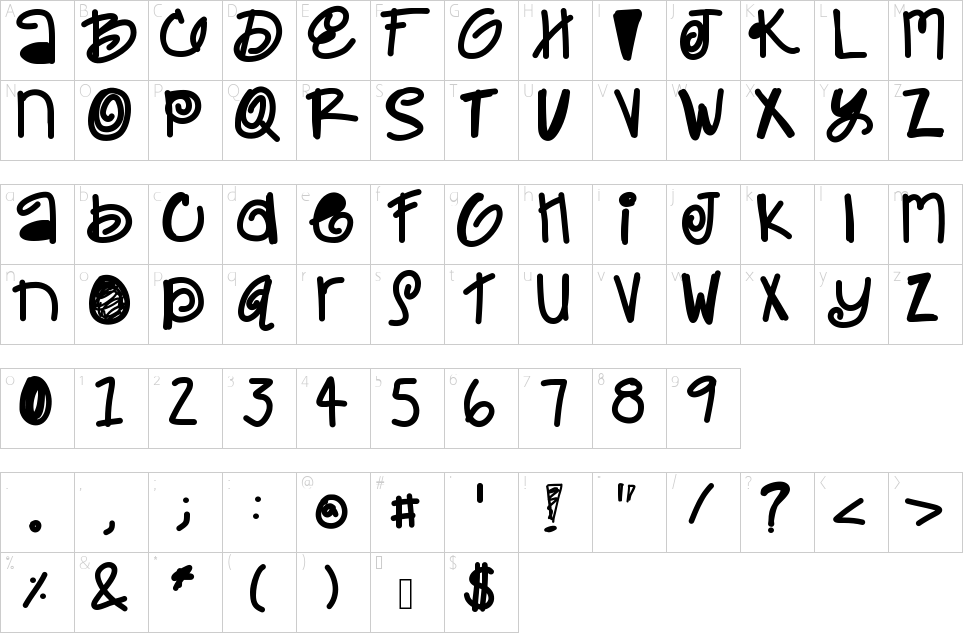
A Maulie é uma fonte grátis disponível para download tanto no Windows quanto no Mac. Desenvolvida por Des Gomez, a fonte Maulie já foi baixada por 1.509 pessoas. Se você busca uma fonte que seja versátil e fácil de usar, a Maulie pode ser a escolha certa. Seu estilo elegante e moderno a torna perfeita para aplicações de design gráfico como logo, flyers, e até mesmo para criação de sites pessoais. Em um ambiente digital cada vez mais cheio de texto, uma fonte clara e atraente como a Maulie pode tornar a sua comunicação visual mais agradável e profissional. Aproveite a liberdade de usar esta fonte grátis, sem ter que se preocupar com custos de licenciamento.